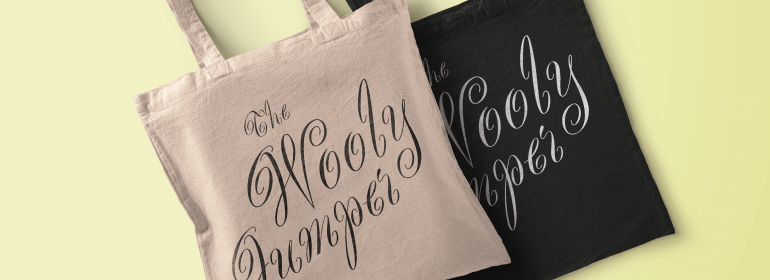
Scriptease™
Scriptease™,这款字体结构工整、笔画清晰,兼顾美观与易读性,适用于标题、正文、海报、包装、LOGO 等多种场景。字形优雅稳定,风格百搭耐看,适配日常排版与创意设计,让文字呈现更舒适、更具质感。Scriptease™一笔一画,皆是细节,以均衡的比例、流畅的线条打造舒适视觉体验,字形端正大气,风格简约现代。无论是商业设计、品牌宣传还是日常排版,都能轻松驾驭,让文字更有格调与力量。Scriptease™字体下载。
字体品牌: ITC(Monotype) 设计师:Grimshaw,Phill 字体分类: 字体属性:外文 字符集:Unicode 发布时间: 2018